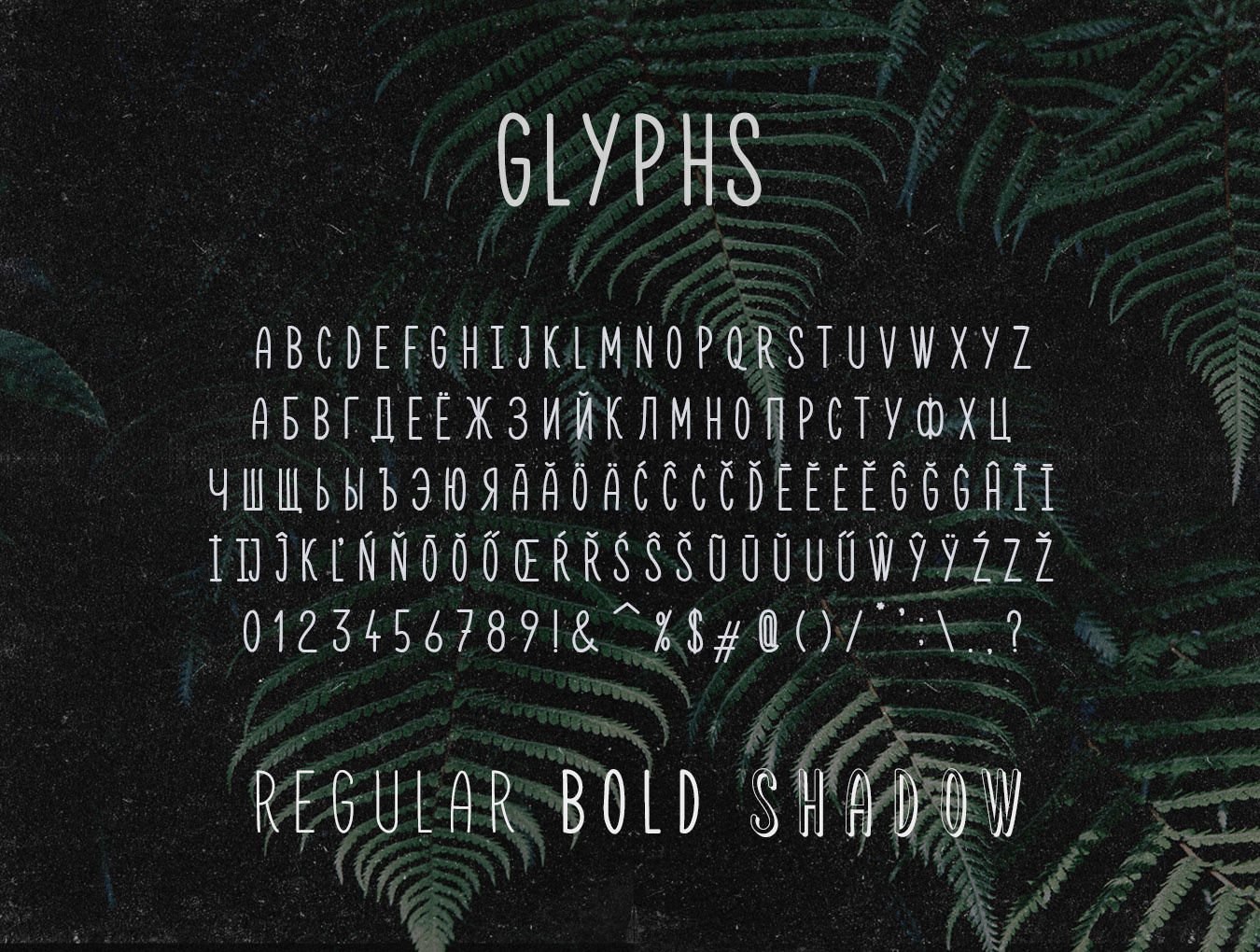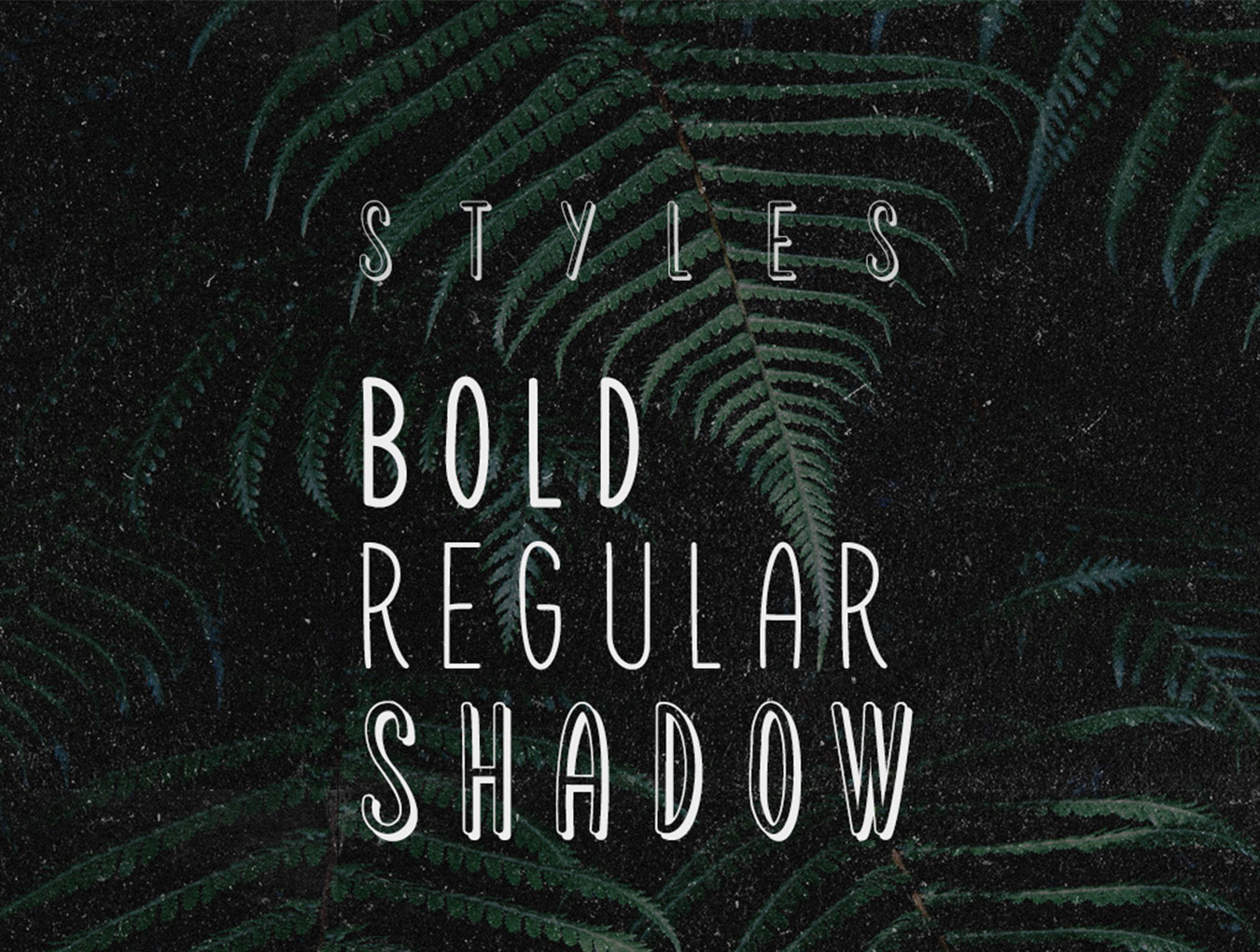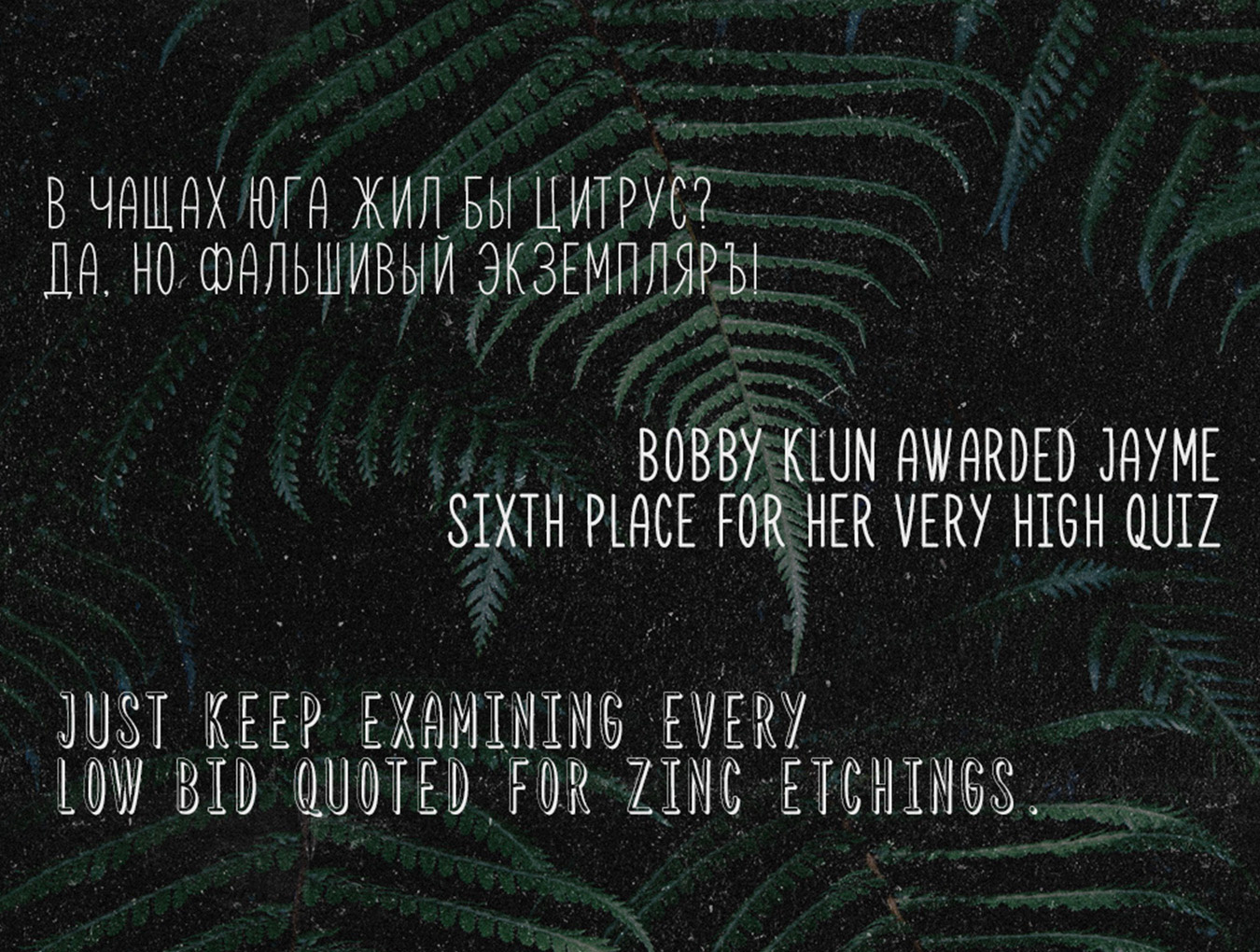
手写字体3种风格,Karmina手写
Handwritten font in 3 styles, Karmina Handwritten
Karmina很漂亮,易于阅读手写字体。我们希望创建最通用,可读和平衡的手写字体,适用于任何类型的设计,适用于各种情况。这个字体包括3种风格;标准,大胆和阴影。 Karmina有3种格式; OTF,TTF和WOFF。